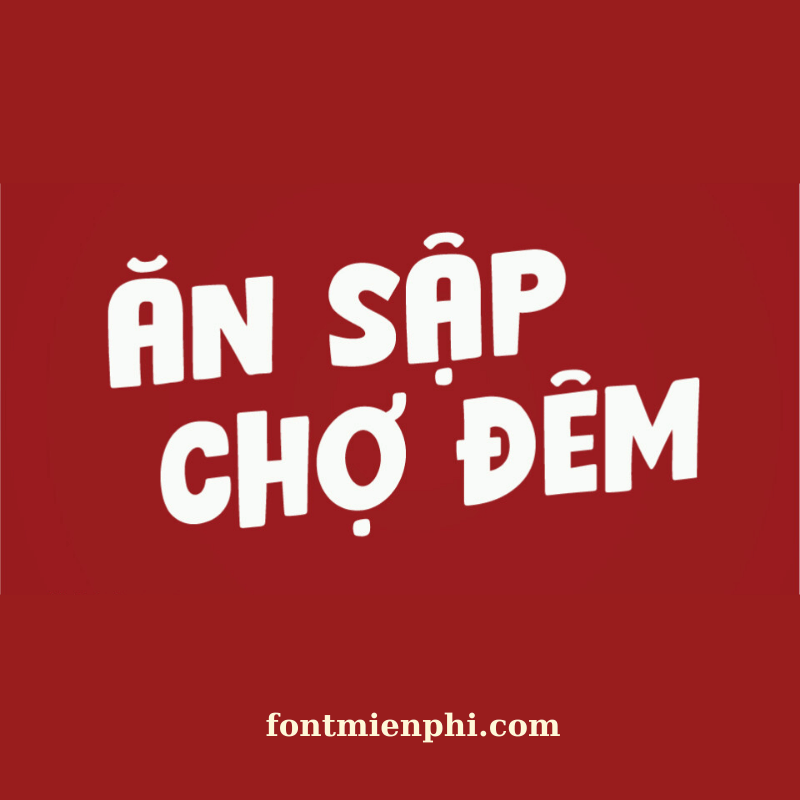
Font Việt hóa 1FTV VIP Hello Roti
Font Việt hóa 1FTV VIP Hello Roti  – Phong Cách Độc Đáo Cho Thiết Kế
Giới thiệu:
Font Việt hóa 1FTV VIP Hello Roti là bộ font chữ nghệ thuật độc đáo, được thiết kế dành riêng cho người dùng yêu thích phong cách sáng tạo, cá tính. Với nét chữ mềm mại, uốn lượn cùng khả năng tương thích tiếng Việt hoàn hảo, Hello Roti trở thành lựa chọn hàng đầu cho dân thiết kế, content creator và những ai đam mê typography.
Đặc điểm nổi bật:
• Thiết kế độc quyền: Phong cách chữ nghệ thuật, đường nét tinh tế, phù hợp với poster, logo, banner.
• Hỗ trợ tiếng Việt: Đầy đủ dấu, không lỗi font, tương thích mọi phần mềm thiết kế.
Lợi ích khi sử dụng:
• Tạo điểm nhấn ấn tượng cho sản phẩm thiết kế.
• Nâng cao tính thẩm mỹ, thu hút người xem.
Kết luận: